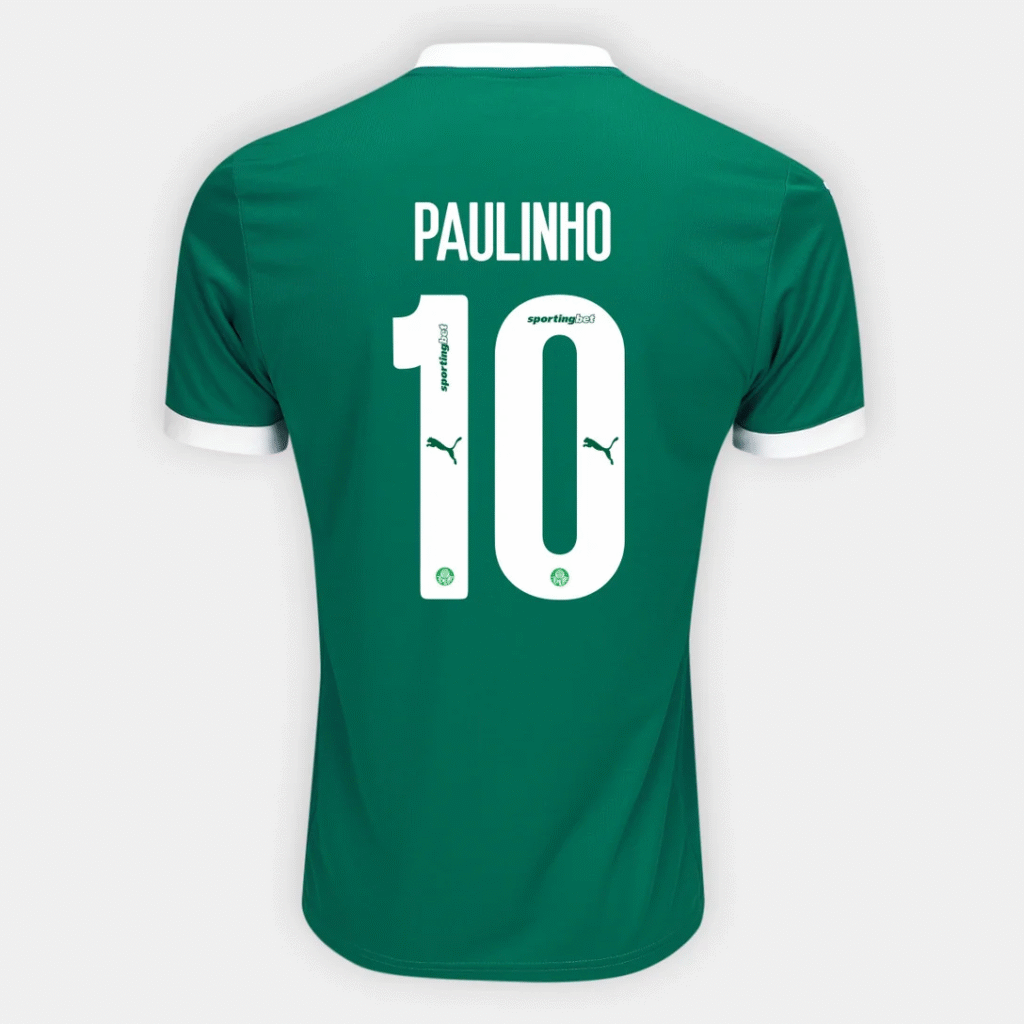
A temporada 2025 chegou e, com ela, os novos mantos da Sociedade Esportiva Palmeiras. Como de costume, a Puma, fornecedora de material esportivo do Verdão, apresentou um design que mistura tradição e modernidade. Um dos detalhes mais procurados pelos designers e torcedores é, sem dúvida, a tipografia oficial usada nos nomes e números das camisas.
Se você busca replicar o visual autêntico do Palmeiras em suas artes, mockups ou projetos pessoais, ter a fonte correta é essencial. Esta é a tipografia que estampa as costas de craques e ídolos no Allianz Parque e nos gramados pelo Brasil.
Estilo e Design da Tipografia
A fonte do Palmeiras para 2025, assinada pela Puma, apresenta um design robusto e moderno. Ela possui linhas retas, com cantos bem definidos e uma leve inclinação (itálico) que transmite uma sensação de velocidade e dinamismo.
Diferente de fontes mais arredondadas, esta tipografia impõe respeito e seriedade, alinhando-se à força do clube. Ela é usada em todo o conjunto de uniformes (principal, visitante e alternativo) da temporada 2025, garantindo excelente legibilidade tanto na TV quanto ao vivo. É uma fonte que equilibra perfeitamente a estética esportiva com a clareza necessária para a identificação dos atletas.